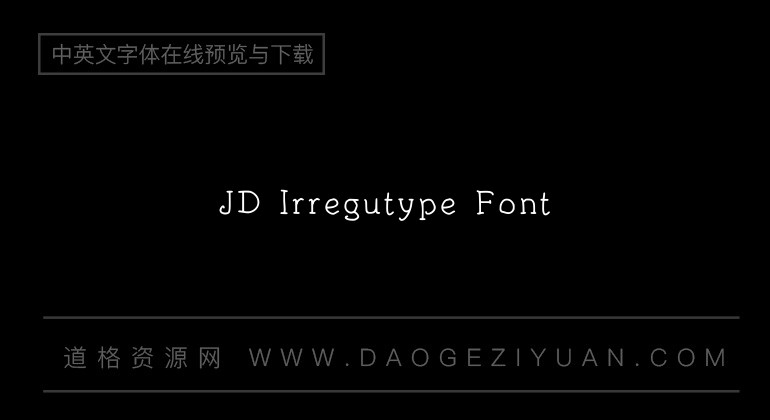
JD Irregutype Font
JD Irregutype Font 是一款由日本设计师 Junichi Doi 制作的不规则字体。它的特点是字母形状不规则,线条粗细不一,给人一种手写的感觉。这种不规则的字体设计在一些场合下非常有用,可以让文字看起来更加有趣和个性化。JD Irregutype Font 适用于设计海报、宣传单、书籍封面等许多创意设计领域,它的设计风格与日本的手写风格、水墨画等文化元素有着紧密的联系,因此在日本的设计界也非常受欢迎。
JD Irregutype Font是一款非常不错的手写艺术字体,具有很好的视觉感,适合于文化类的宣传设计、商业类品牌的广告和产品包装设计以及个性化文字排版等较多场景。